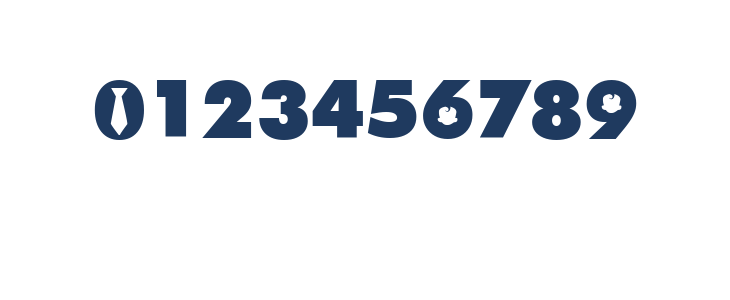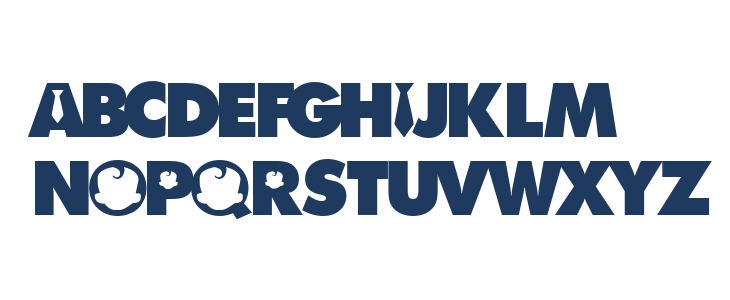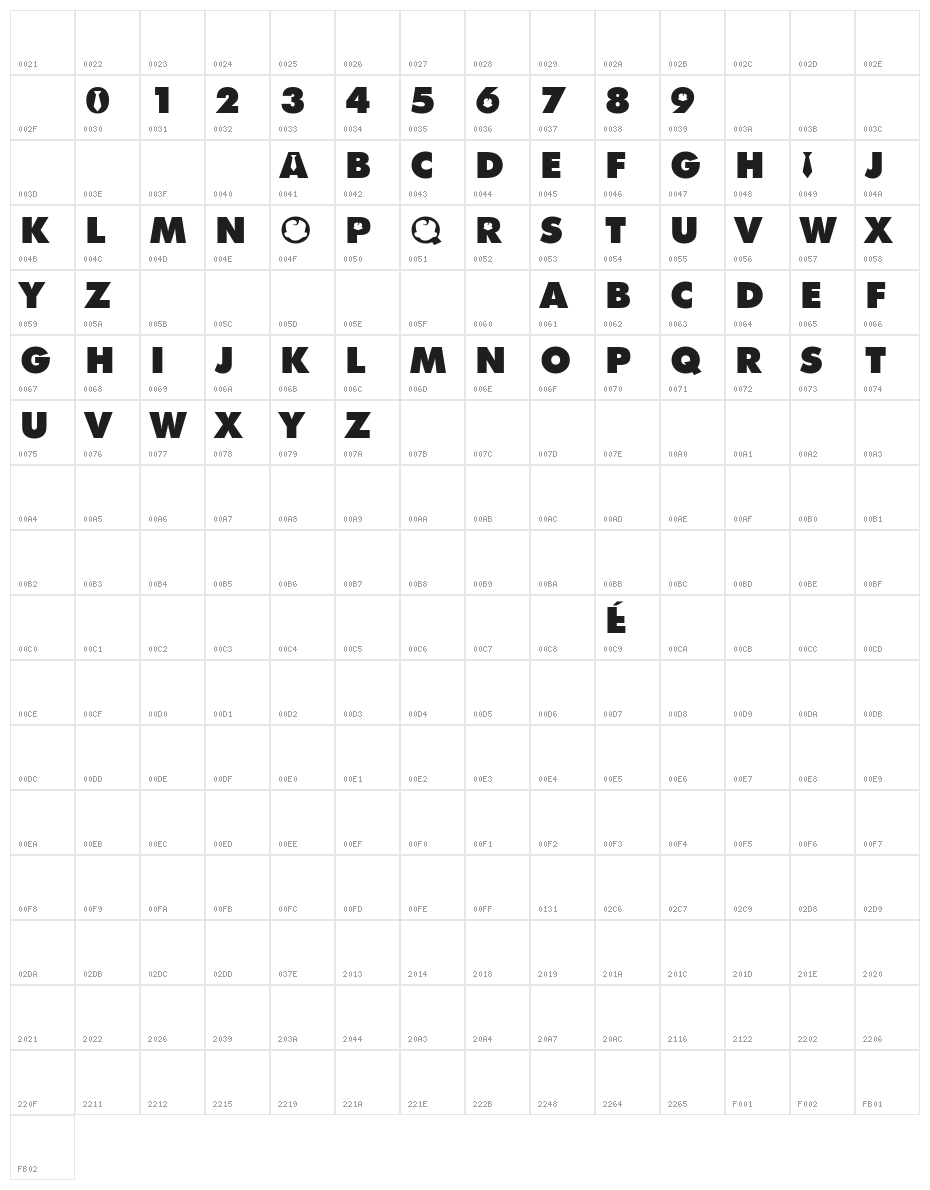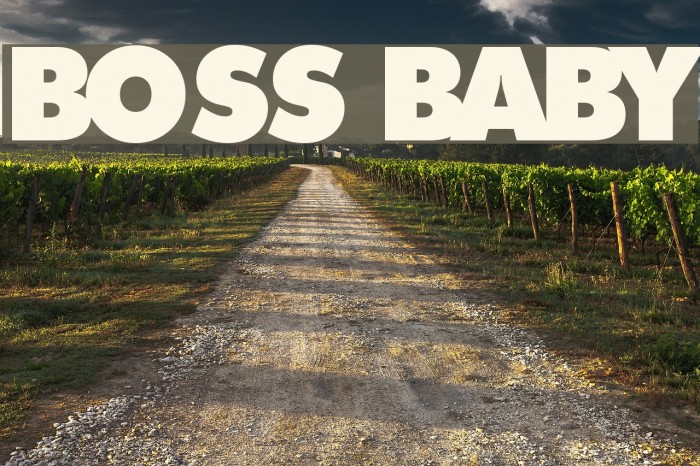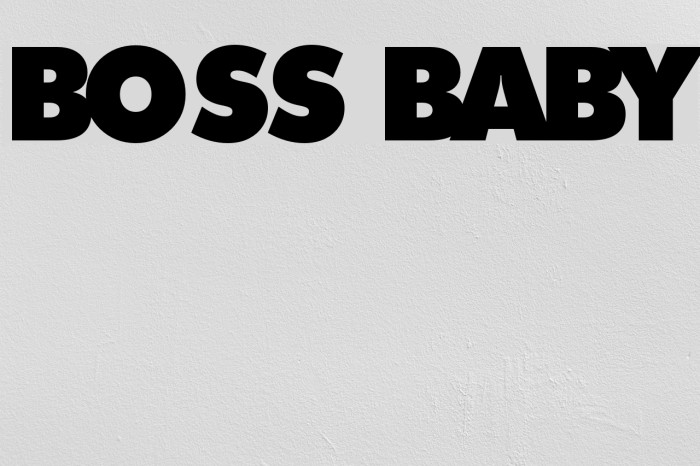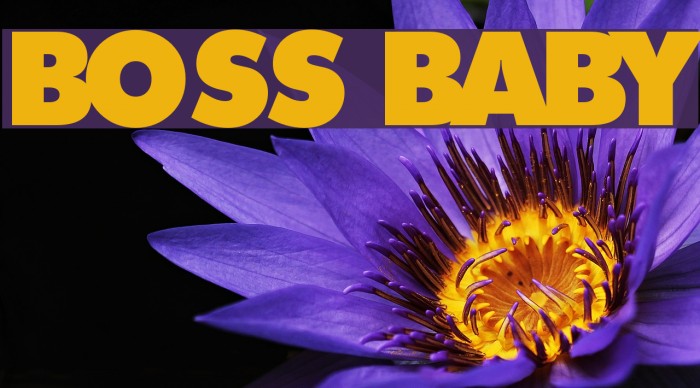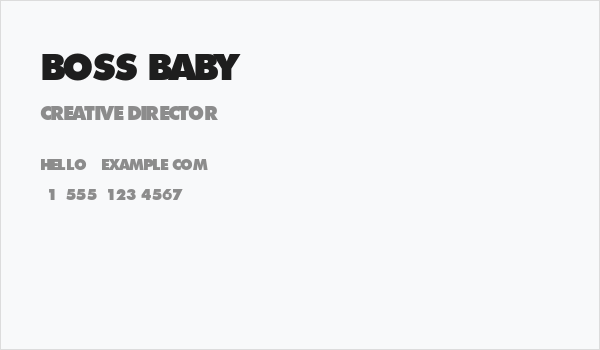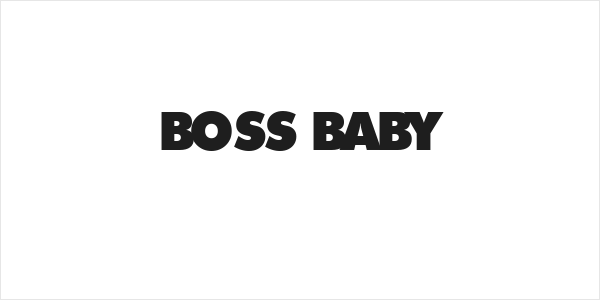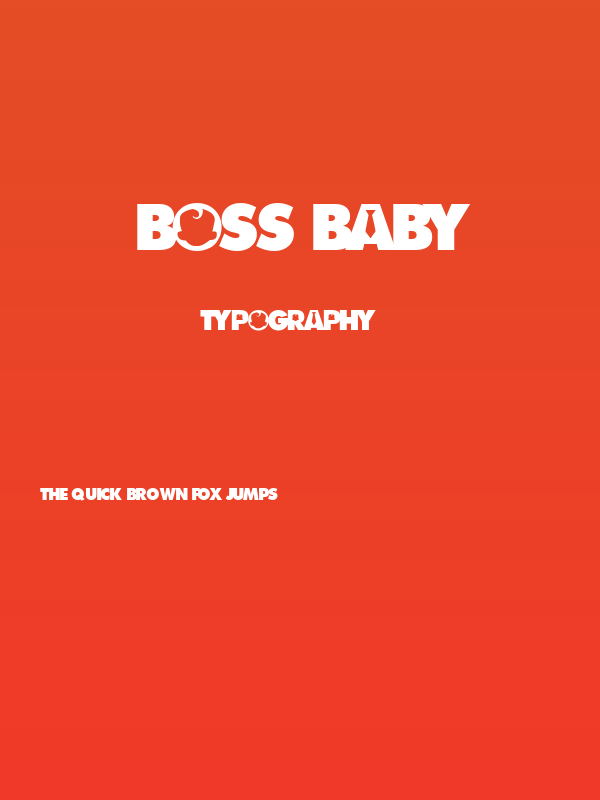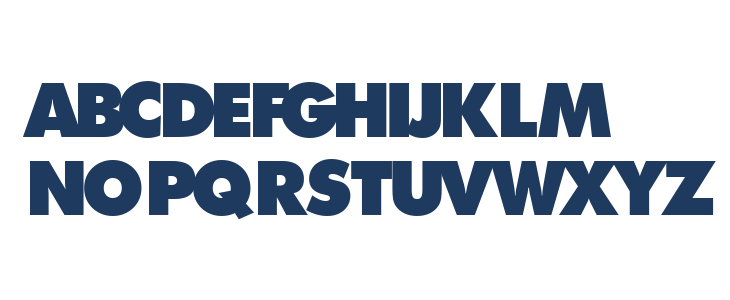
Boss Baby Font
BOSS-BABY 大写
BOSS-BABY 小写
BOSS-BABY 其它煤焦
| 名称 | Boss Baby |
| 分类 | Kids |
| 整体风格 | Playful, Modern |
| 推荐项目 | Ideal for children's book covers, playful branding, movie posters, and any project needing a fun, bold typeface. |